Glyphsでのアラビア語フォント作成に関する、手っ取り早く簡単な入門書をお探しでしたか?これがそうです。
ドキュメントを設定する
Glyphsを起動すると、スタートウィンドウが表示されるか、後からいつでもファイル > グリフセットから新規作成で表示できます。
ドキュメント作成ダイアログで、含めたいスクリプトを選択するだけです。手始めに、まずアラビア語を選択することをお勧めします。スクリプトはアルファベット順にリストされているので、ローカライズによっては通常、一番上に表示されます。次に、グリフを準備するオプションをオンにします。
…そして、含めたいアラビア語のサブセクションを選択します。手始めに、基本シェイプ、そしておそらく基本も選択することをお勧めします。
まだ選択していないものについて心配する必要はありません。後からいつでもグリフを追加できます。方法は次の通りです。空のドキュメントから始めても、複数の方法でグリフを追加できます。最も簡単な方法は、フォントビュー(Cmd-Opt-1)のサイドバー経由です。言語セクションで、アラビア語を開き(まだリストにない場合はプラスボタンで追加)、数字バッジが付いたサブセクション、例えば基本シェイプを右クリックし、表示される不足しているグリフのリストから追加したいグリフを選択するか、単にすべてを選択します。
次に生成を押して、選択したグリフをフォントに追加します。このセクションが完了したことを示すために、フォントにすべてのグリフが含まれると、数字バッジはチェックマークに変わります。
ヒント
Glyphsが「uni0627」や「afii57415」のような名前ではなく、alef-arのような人間が読める名前を使用していることに気づくでしょう。ご想像の通り、-arという接尾辞は、そのグリフがアラビア文字に属することを示します。書き出し時には、名前はいわゆる「プロダクションネーム」に変換され、OTFで期待される形式になります。しかし、Glyphs内で作業している間は、それについて心配する必要はありません。
基本シェイプから始める
さて、サイドバーでアラビア語 > 基本シェイプを選択し、フォントビューに関連するグリフのみが表示されるようにしましょう。もちろん、何から始めても構いませんが、基本シェイプは他のグリフで頻繁に再利用されるシェイプを含んでいるため、始めるのに良い場所です。
私は「ドットなしのbeh」から始めるのが好きです。アラビア語が読める方なら、「待って、ドットのないbehなんてないよ、behにはいつも下にドットがあるじゃないか」と言うかもしれません。そして、もちろんその通りです。しかし、少しの間、behからドットを取り除いたと想像してみてください。そうすると、tehやpeh、さらにはyehやnoonの位置に応じた形にも再利用できるシェイプが出来上がります。理にかなっていますよね。そして、それこそが私たちが「基本シェイプ」と呼んでいるものです。
私たちが探しているグリフはすべてbehDotless-arと呼ばれ、アラビア文字のドットなしのbehを示します。そして、位置に応じたバリアントには、終端形(final or terminal position)には.fina、中間形(medial position)には.medi、語頭形(initial position)には.initという追加のドット接尾辞が付きます。接尾辞のないものは独立形です。4文字の接尾辞は、もし疑問に思っていたなら、同じタグを持つOpenTypeフィーチャーに対応しています。では、それらを見つけて選択しましょう。
…そして、(すでに持っているフォントタブとは別に)新しい編集タブでそれらを開きます。表示 > 新規タブを選択するか、対応するキーボードショートカットCmd-Tを押します。
ヒント
もしこれがGlyphsでの初めての作業なら:表示されているグリフのいずれかをダブルクリックして編集用に開きます。テキストツール(ショートカットT)に切り替え、入力を開始したり、矢印キーやマウスクリックでカーソルを移動させたり、Shiftキーを押しながら矢印キー(またはShiftキーを押しながらクリック)でテキストを選択したりします。タイピング、コピー、ペーストは、他のテキスト入力と同様に期待通りに機能します。編集ビューでできることについてさらに詳しく読む。
さて、ドットなしのbehの4つのバリアントが、この編集タブに並んで書かれているのがわかります。そして、独立形のbehDotless-arが左側で編集用に開かれています。混乱しないでください。4つのグリフはすべて空っぽです。あなたが見ている灰色のシェイプは単なるプレースホルダーで、まだ空のうちはグリフを識別しやすくするためのものです。中に何かを描くとすぐに消えます。
では、独立形のドットなしのbehを描き始めましょう。良い出発点は、描画ツール(ショートカットP)でスケルトン線を描き、縦のメトリクスを参考にすることです(表示 > メトリクスを表示、Cmd-Shift-M、および表示 > メトリクス名を表示)。
パス > 極点を追加で極点を追加し、パス > パスを整頓(Cmd-Shift-T)でパスをきれいにしたり、選択ツール(ショートカットV)で個々のノードを選択してキーボードのDeleteキーを押して削除したりします。最終的にはこのようになるかもしれません。
ヒント
良いベクターパスを描くことについては、もっとたくさんのことがあります。良いパスを描くチュートリアルで詳しく読んでください。
スケルトンが完成したら、フィルター > パスのオフセットでそれを拡張できます。ストロークを作成オプションを使用し、他の値を試してみてください。
灰色の情報ボックス(表示 > 情報を表示、Cmd-Shift-I)でサイドベアリングを設定するのを忘れないようにしましょう。左サイドベアリング(LSB)に50を使い、右サイドベアリング(RSB)にメトリクスキー=|でそれをミラーリングします。
=|は、反対側のサイドベアリングの値を取り、現在のサイドベアリングで使用します。したがって、RSBではLSBのショートカットであり、逆もまた同様です。グリフ幅の中央に描画を配置する最も簡単な方法です。最終的にはこのようになるでしょう。
ヒント
サイドベアリングを見つけるプロセスであるスペーシングに関するチュートリアルを読んで、それをより快適にするためのすべてのキーボードショートカットと小さなコツを学びましょう。
美しい!さて、グリフ > アンカーを設定(Cmd-U)でアンカーを追加する必要があります。アンカーは、ドットや母音記号が接続できる位置を示します。これは後でtehやbehを構築するために重要になります。選択ツール(ショートカットV)で、それらを大まかな位置に移動させます。このようになります。
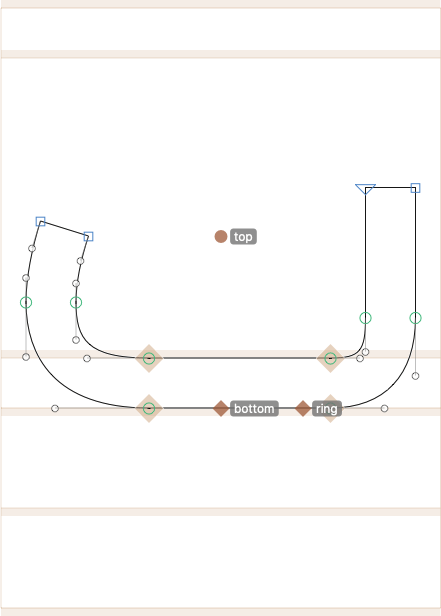
topアンカーは文字の上にくるドットや母音記号を接続するためのもので、ご想像の通り、bottomという名前のアンカーは文字の下にくるすべてのドットや記号のためのものです。ringアンカーはパシュトー語の文字teh with ring (U+067C)用です。パシュトー語のサポートを計画していない場合は、ringアンカーを削除しても構いません。
位置に応じたシェイプ
接続部分のメトリクス
上で少し触れましたが、デフォルトでは接尾辞のないグリフが独立形と見なされます。もちろん、アラビア語では多くの文字が、終端形、中間形、語頭形など、他の可能な位置に応じたバリアントの一部またはすべてを持っています。これらはグリフ名のドット接尾辞で区別します。私たちはすでにbehDotless-arの位置に応じたバリアントを画面上に持っていますが、まだ空です。
デザイン的には、位置に応じたバリアント間でパスをたくさんコピー&ペーストすることができます。なぜなら、それらは異なっていても、接続するストロークを除けば、多くの類似点があるからです。それらの接続ストロークはすべて同じ高さにある必要があり、それによって位置に応じたシェイプが適切にかみ合い、接続された単語を形成できます。
接続ストロークの下端はベースラインと呼ばれ、その上端はジョイニングラインの高さと呼ばれます。ベースラインはy座標ゼロで定義され、多くの書記体系で共通ですが、ジョイニングラインの高さはアラビア語に特有で、その値は私たちが作成したストローク幅と同じです。ジョイニングラインの高さはファイル > フォント情報 > マスター > メトリクスで設定できます。
それぞれの線をクリックすると、メトリクスの名前とグリフの適用範囲を変更できるダイアログが表示されます。幸いなことに、私はジョイニングラインとアラビア語スクリプトのデフォルトのままで大丈夫です。線上で直接、位置(デフォルト100)とそのオーバーシュート(デフォルト16)を変更できます。あなたのデザインにとって意味のある他のメトリクスを追加することを検討してください。例えば、非常に幾何学的なデザインでは、文字によく現れる1つまたは2つのストロークの高さを追加するかもしれません。
位置に応じたバリアントの描画
クールですね。これで全てが整ったので、あとは一つの位置に応じたシェイプから次のシェイプへパスをペーストし、必要な調整をするだけです。覚えておいてください:グリフをダブルクリックして編集用に開きます。ストロークの終端がサイドベアリングにぴったりと合うようにしてください。つまり、接続するストロークの終端のサイドベアリングをゼロにします。
各グリフにアンカーを追加し、配置するのを忘れないでください。見た目は良いですが…まだ終わりではありません。
ストロークの終端
接続ストロークの端に小さなオーバーラップを追加する必要があります。なぜでしょうか?文字が接続する部分で、ごくわずかでありながらも気になるアーティファクトを表示するレンダラーで問題が発生するからです。
では、ストロークを伸ばすだけではダメなのでしょうか?いいえ、それでは事態を悪化させます。
したがって、文字が接続する場所では、ノードが互いにはまり込む必要があります。ストロークの端の中央で延長する必要があります。経験上、ストロークの端に半円または単に尖った三角形のシェイプが最も効果的です。
どのシェイプを選ぶにせよ、フォント全体で一貫性を保つのが良い考えです。そうしないと、文字が接続する際にさまざまなアーティファクトが発生してしまいます。もちろん、これらの終端を自分で描画し、管理することもできます。しかし、最終的には何百、何千ものコネクタを扱うことになるので、そのストロークの終端を一度描画して、毎回均一に再利用できれば、何時間もの作業を節約できるのではないでしょうか?
さて、今日はあなたにとって幸運な日です。なぜなら、Glyphsにはまさにその機能が組み込まれており、それはセグメントコンポーネントと呼ばれています!本質的に、これはホストシェイプ内のパスセグメントを置き換える開いたパスです。方法は次の通りです。グリフ > グリフを追加(Cmd-Shift-G)を選択し、表示されるダイアログシートにセグメントグリフの名前を入力します。名前は_segmentで始まり、その後に任意のドット接尾辞が続きます。例:_segment.strokebutt
サンプルフォント:Nadine Chahine氏によるMakdessi。ワークフローの再現の参考にも使用しました。